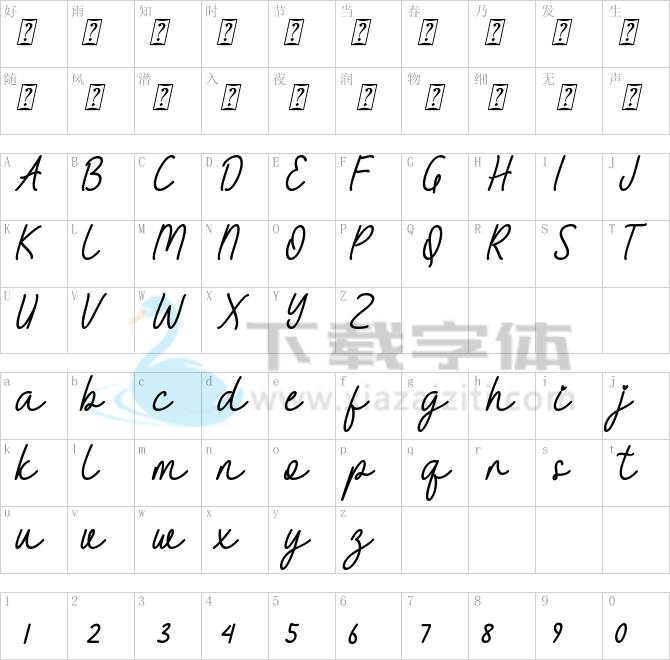
Amelline.ttf字体下载,这款字体结构工整、笔画清晰,兼顾美观与易读性,适用于标题、正文、海报、包装、LOGO 等多种场景。字形优雅稳定,风格百搭耐看,适配日常排版与创意设计,让文字呈现更舒适、更具质感。Amelline.ttf字体下载一笔一画,皆是细节,以均衡的比例、流畅的线条打造舒适视觉体验,字形端正大气,风格简约现代。无论是商业设计、品牌宣传还是日常排版,都能轻松驾驭,让文字更有格调与力量。Amelline.ttf字体下载字体下载。
Amelline.ttf图片展示